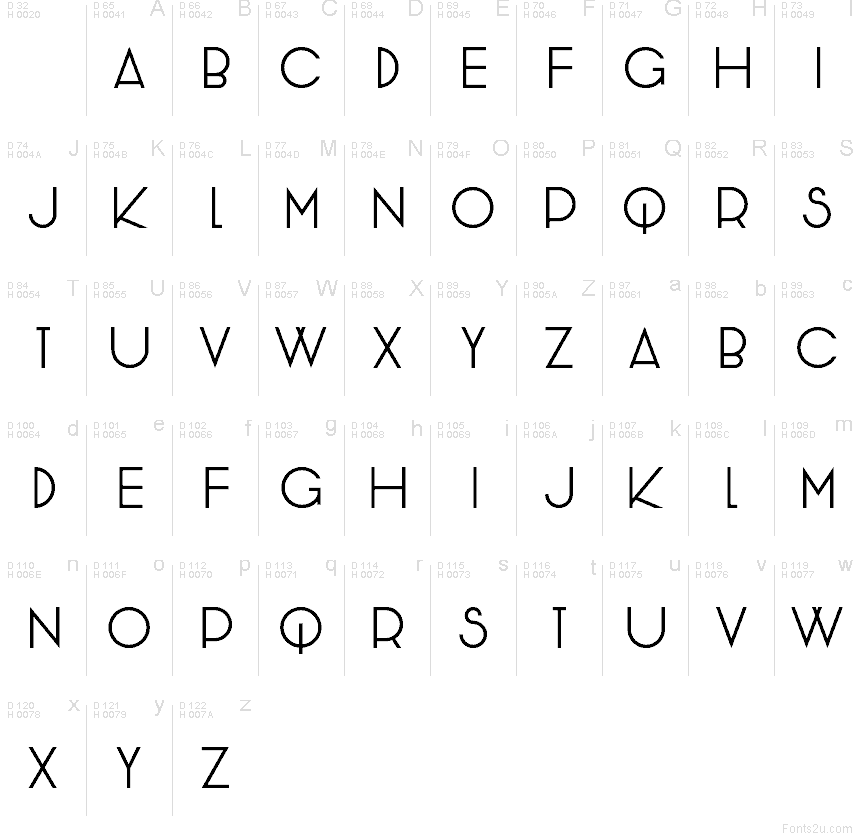
Travesta Flat autorstwa Vladimira Nikolica to darmowy, retro krój typu display z nutą stylu Art Deco. Wielkie litery sprawiają wrażenie wysokich, oszczędnych i architektonicznych, zbudowanych z czystych pociągnięć i szerokich łuków, które nadają znakom wyważony, plakatowy rytm, zamiast miękkości czy zabawy formą.
Świetnie pasuje do brandingu, opakowań, nagłówków w czasopismach, plansz tytułowych i oznaczeń, gdzie cool vintage musi pozostać czytelny i przejrzysty. Jako darmowy font, sprawdza się również w krótkich nagłówkach i monogramach, ponieważ wąskie, smukłe litery tworzą wyrazistą sylwetkę bez potrzeby dodawania ozdobników.